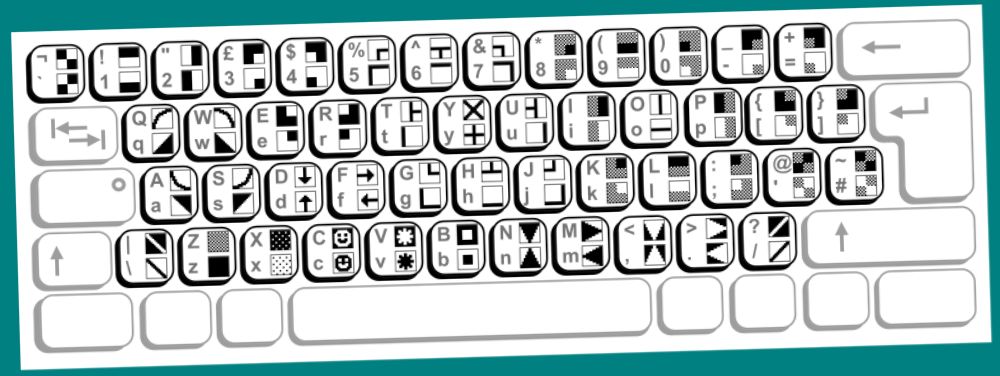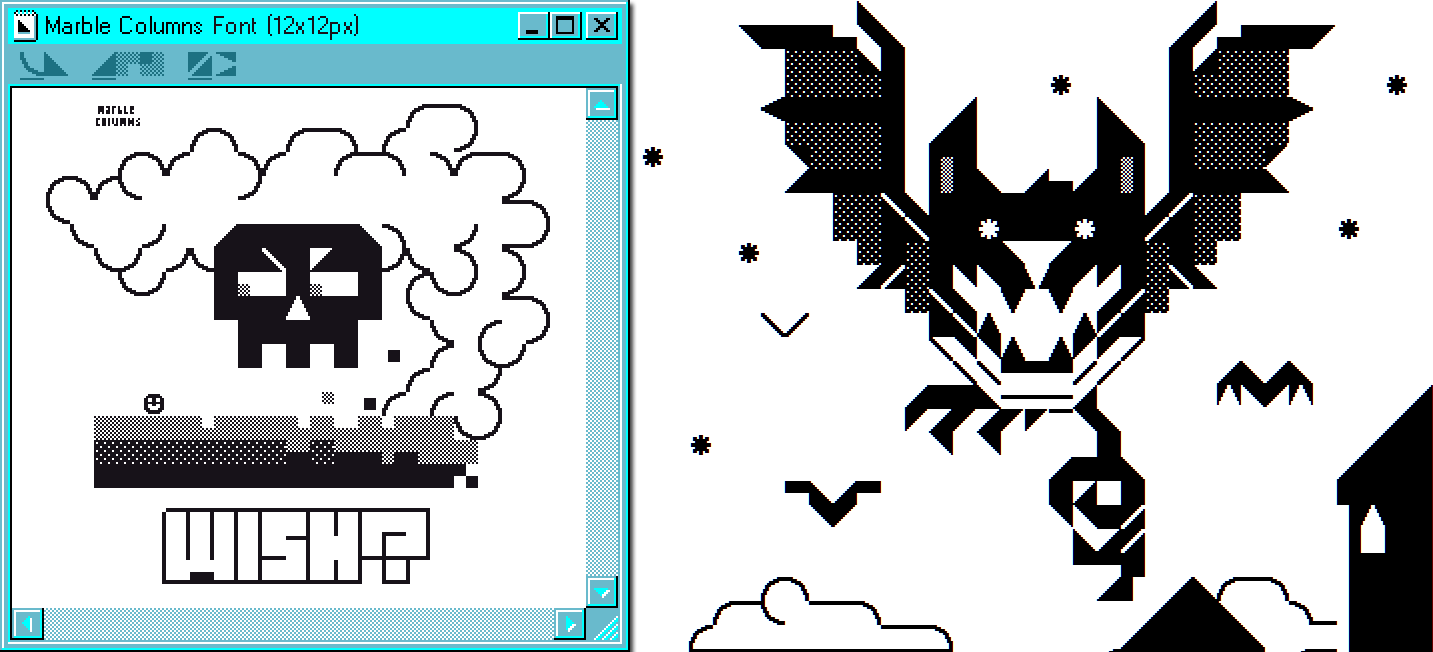
Шрифт «Marble Columns» для отрисовки графики в играх
Polyducks выпустил в продажу пакет «Marble Columns» — это моноширинный шрифт размером 12x12 пикселей, специально созданный для отображения графических элементов в текстовом режиме (аналогично популярному графическому шрифту Wingdings).